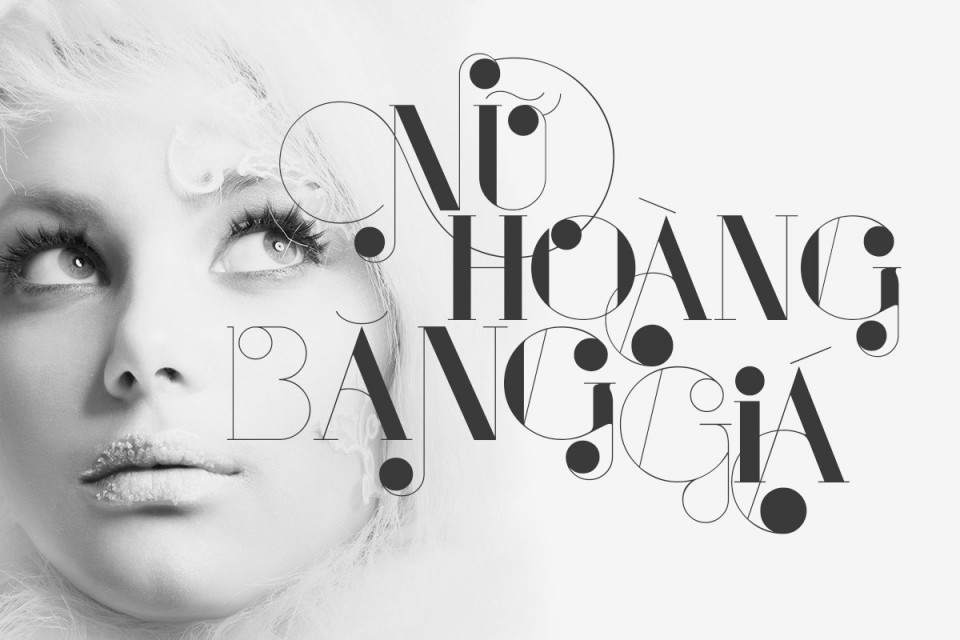
Giới thiệu về bộ Font việt hóa iCiel Port
Trong thế giới thiết kế đồ họa hiện nay, việc lựa chọn một Font Chữ phù hợp đóng vai trò quyết định đến tính thẩm mỹ của sản phẩm. Font việt hóa iCiel Port là một trong những bộ font mang phong cách hiện đại, thanh lịch và cực kỳ linh hoạt. Được tinh chỉnh kỹ lưỡng để phù hợp với hệ thống dấu tiếng Việt, bộ font này giúp các bạn học sinh và nhà thiết kế không còn lo lắng về lỗi hiển thị văn bản khi làm bài tập hay dự án sáng tạo.
Tại sao nên sử dụng Font việt hóa iCiel Port?
Đặc điểm thiết kế tinh tế
Bộ font này sở hữu những đường nét mảnh mai nhưng vẫn giữ được sự chắc chắn, tạo cảm giác sang trọng cho người xem. Font việt hóa iCiel Port rất phù hợp để sử dụng trong thiết kế bìa sách, poster sự kiện trường học hoặc các bài trình chiếu thuyết trình cần sự chuyên nghiệp. Sự cân bằng giữa các nét chữ giúp nội dung trở nên dễ đọc và bắt mắt hơn trên nhiều nền tảng khác nhau.
Khả năng ứng dụng đa dạng
Không chỉ giới hạn trong in ấn, font chữ này còn hoạt động hoàn hảo trên các ứng dụng di động và website. Nhờ quá trình việt hóa chuẩn, các ký tự đặc biệt như “ơ”, “ư” hay các dấu thanh được đặt vị trí chính xác, tạo nên sự hài hòa tổng thể cho đoạn văn bản. Đây là lựa chọn lý tưởng cho những ai yêu thích phong cách tối giản nhưng vẫn muốn tạo điểm nhấn riêng biệt.